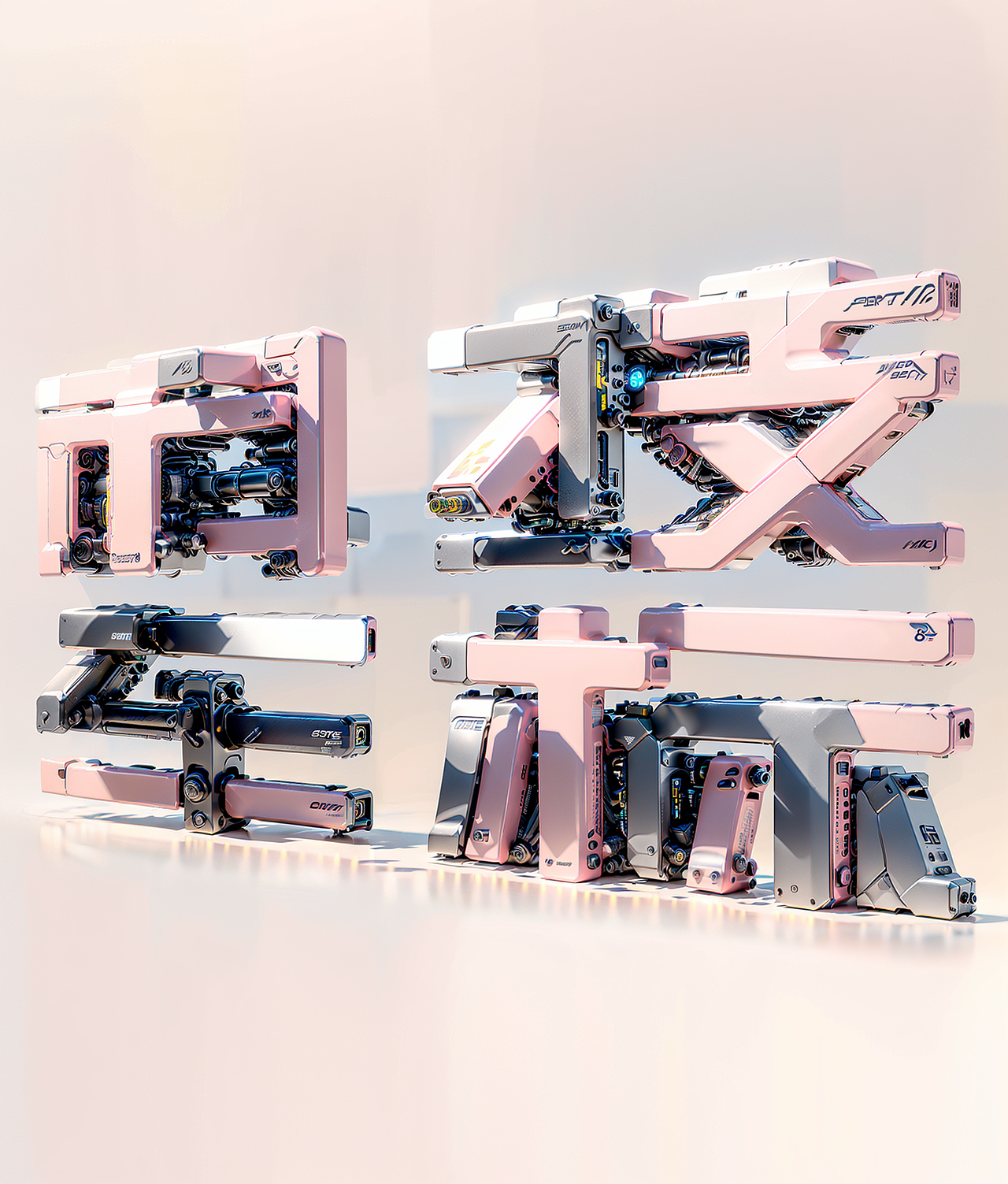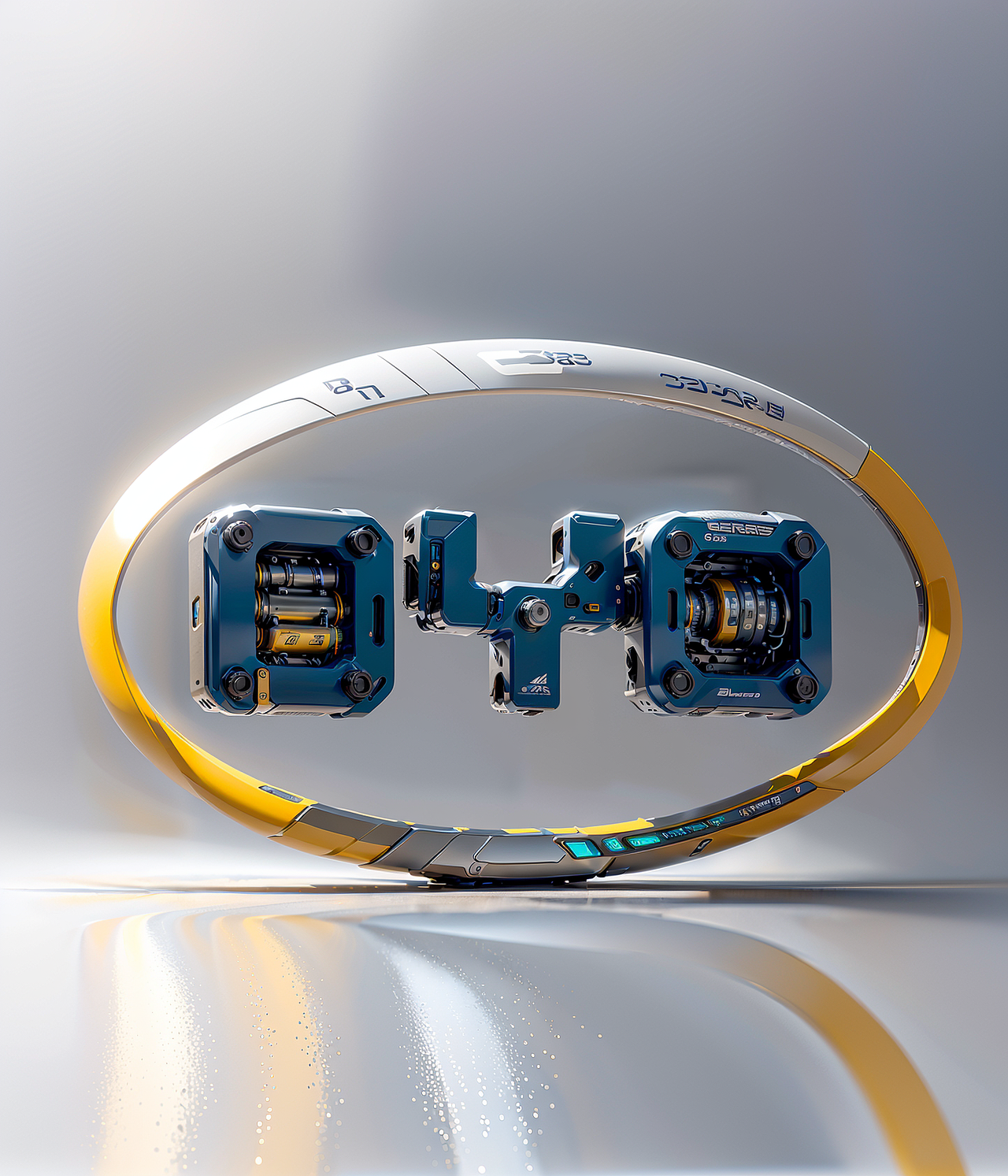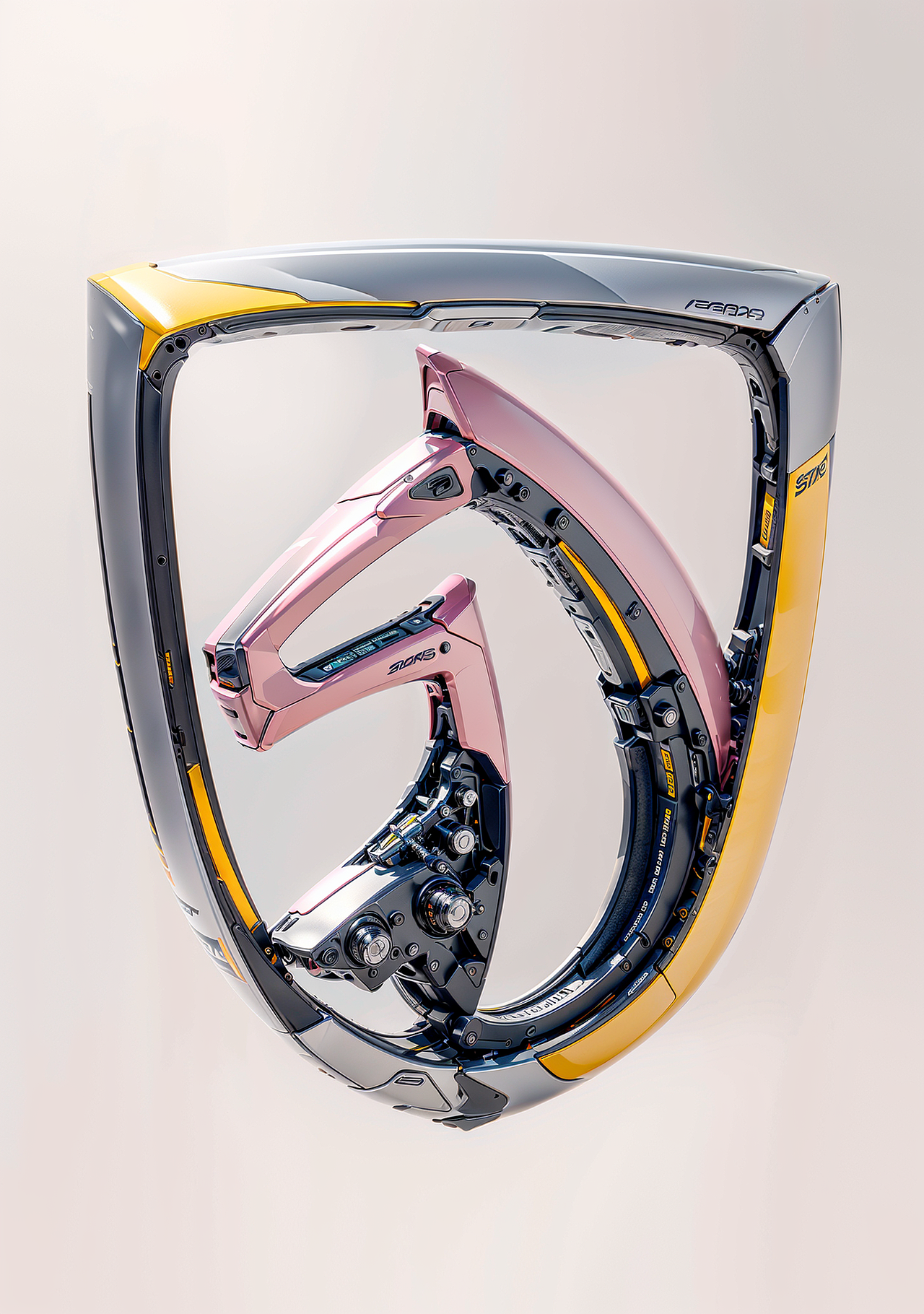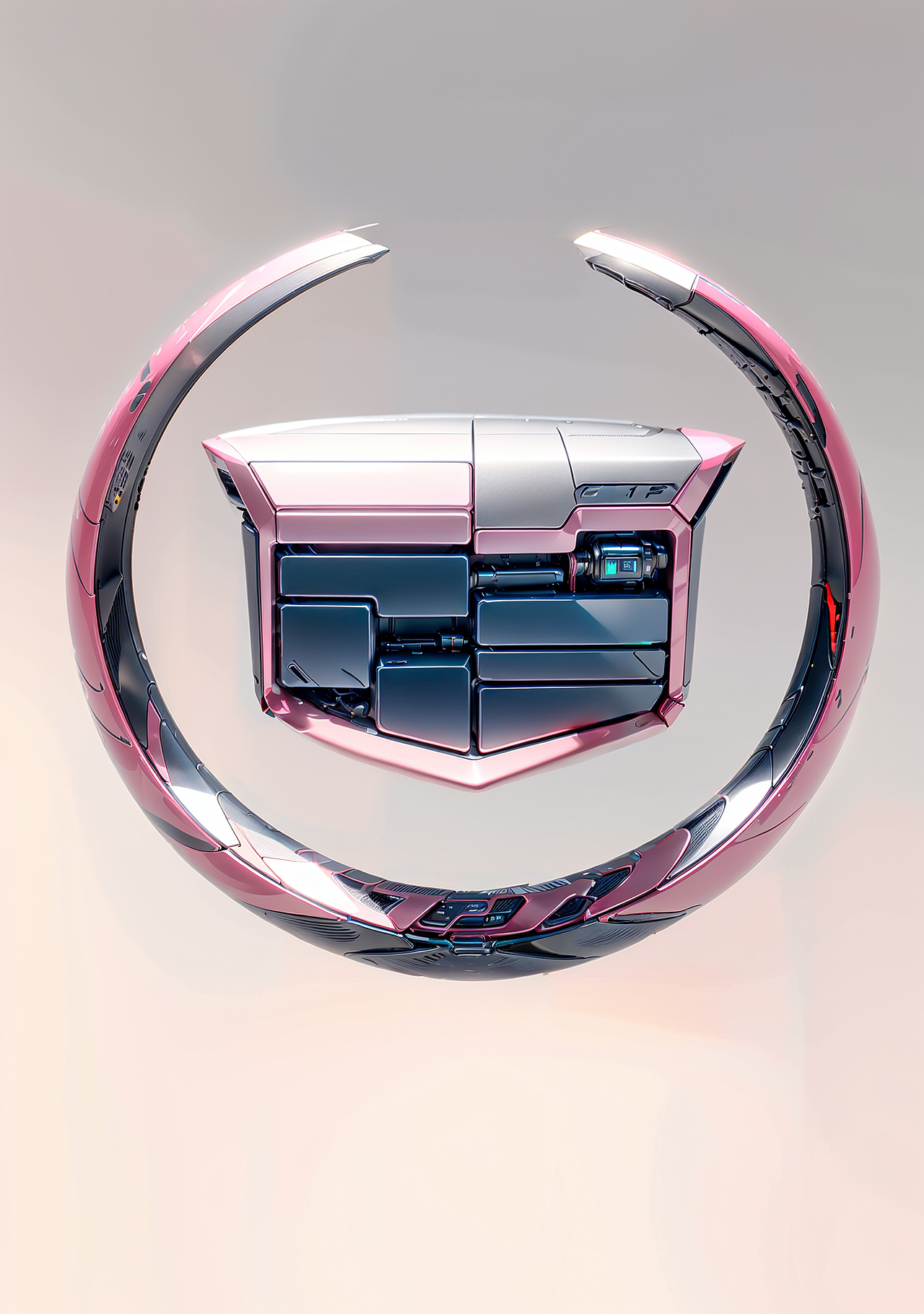
🚀AIGC 重塑车标字体,汽车美学新突破!
AIGC 重塑车标字体,汽车美学新突破!
AIGC 在车标字体设计领域掀起的风暴!!! 工具:liblib 大模型(model)ReVAnimated_v122
采样(sampler)DPM++ 2M SDE Karras
LORA: AIGC朋克机甲字体,
相关性(CFG scale)8步数(steps)30 随机种(seed)0
正向关键词:Sci-fi_jj_(\font\),(white background:1.1),(yellow | silver gray | technology blue:1.2),(morandi color:1.1),machine,miniature,metal,(a mecha-shaped text pattern:1),concept machinery artist,mecha,(simple background:1.1),((best quality)),((masterpiece)),8k,
反向:NSFW,(worst quality:2)(low quality:2),(normal quality-2).lowres,normal quality,(monochromel)(grayscalel),skinspots,acnesskinblemishes,agespot,(ugly:1.331),(duplicate:1.331),(morbid:1.21),(mutilated:1.21),(tranny:1.331),badhandv4-AnimeIllustDiffusion_badhandv4,bad map repair bad-picur